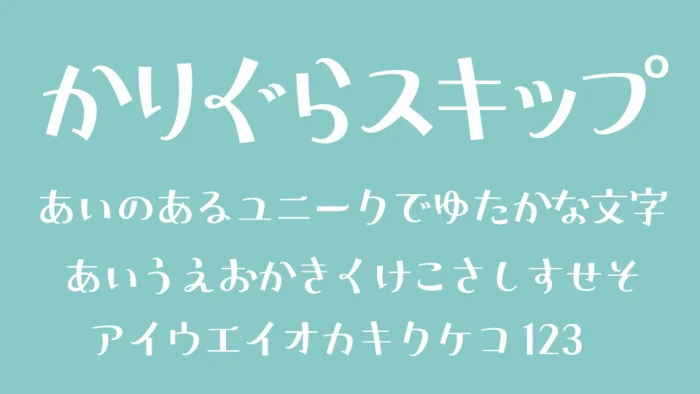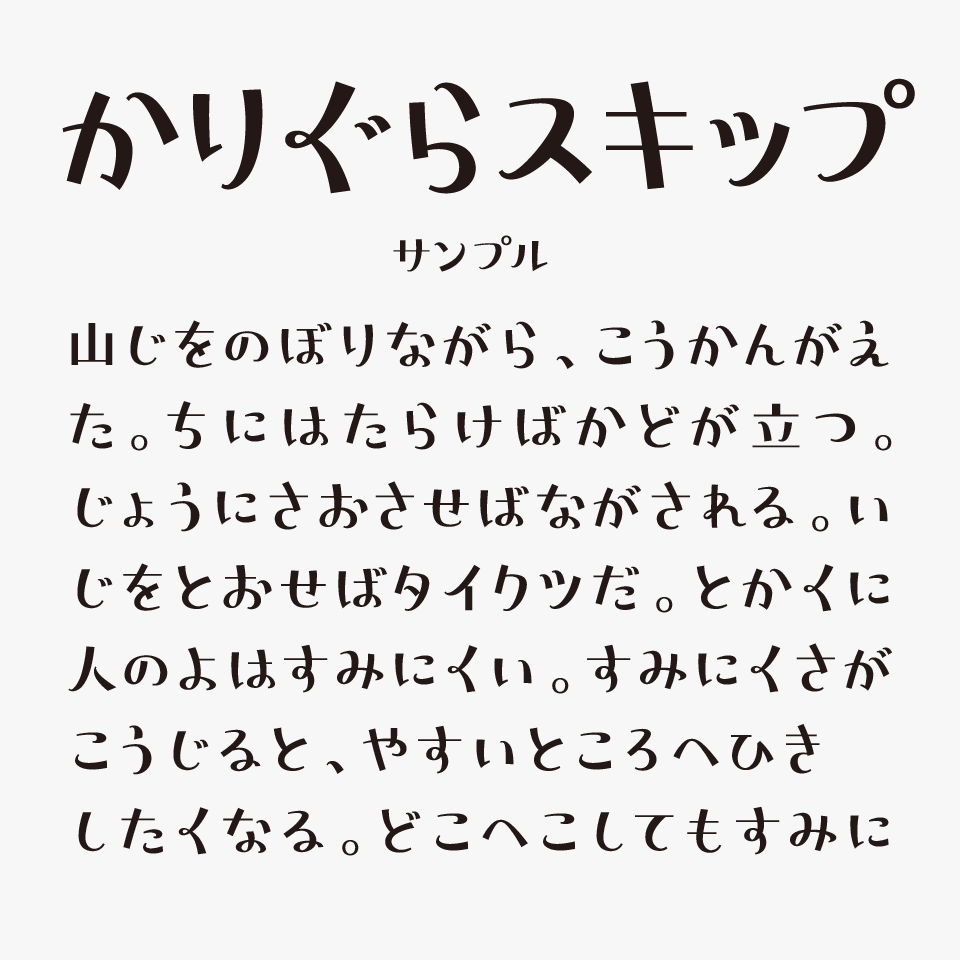
かりぐらスキップ
かりぐらスキップフォントは、カリグラフィーペンで書いたような手書き感が魅力の、線にしっかりと強弱がついたデザインフォントです。
フォント名のとおり、文字がスキップしているような軽快なハネやリズム感が特徴で、一文字ごとに楽しげな動きがあります。
流れるような曲線と、ぴょんと跳ねるようなアクセントが心地よく、見ているだけでも楽しくなるような可愛らしさがあるフォントです。